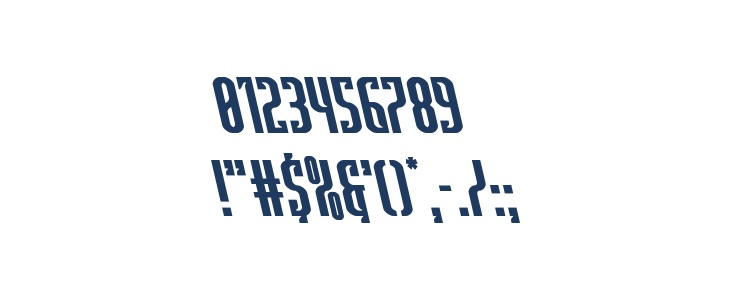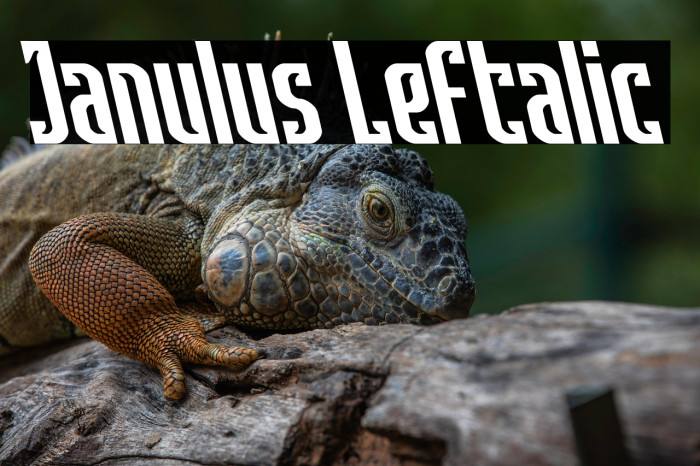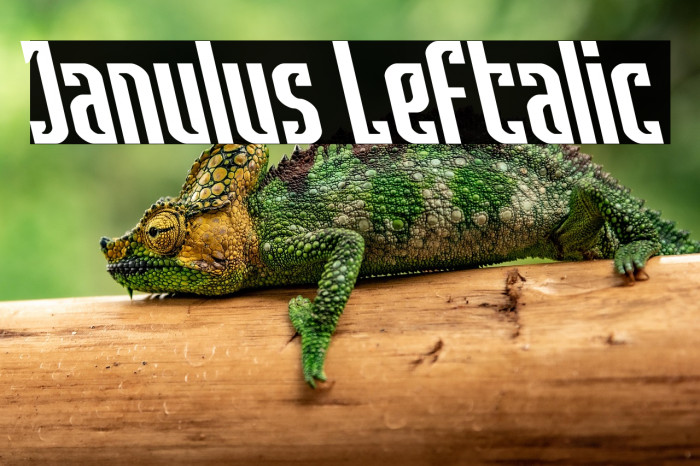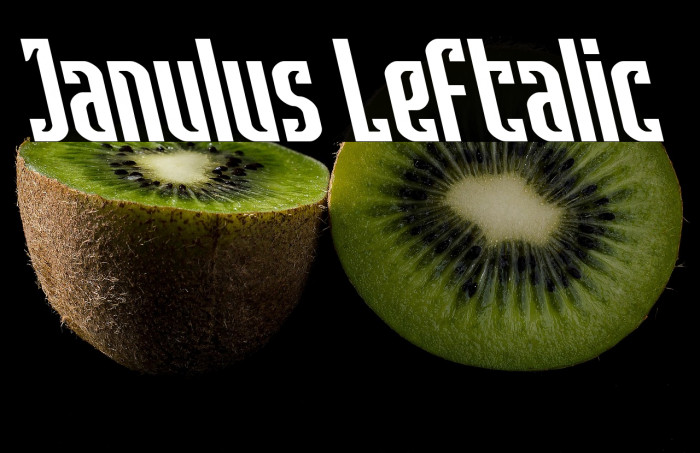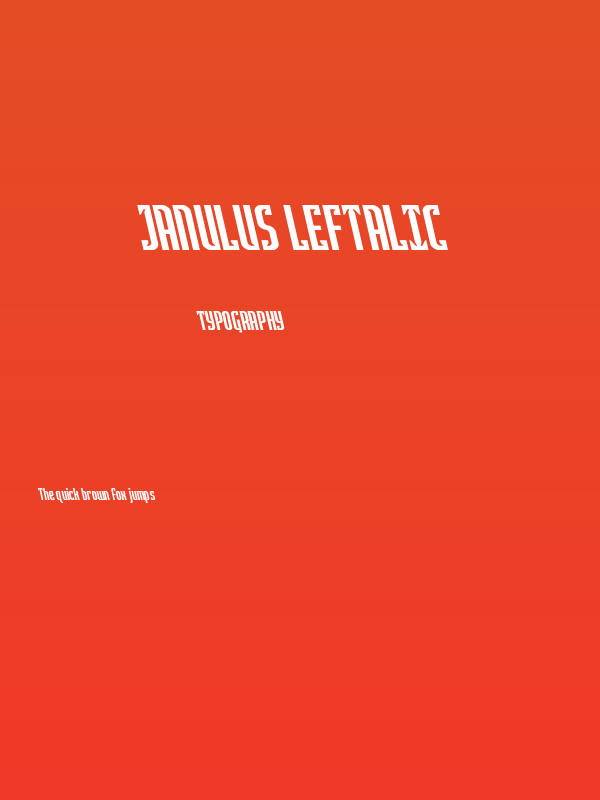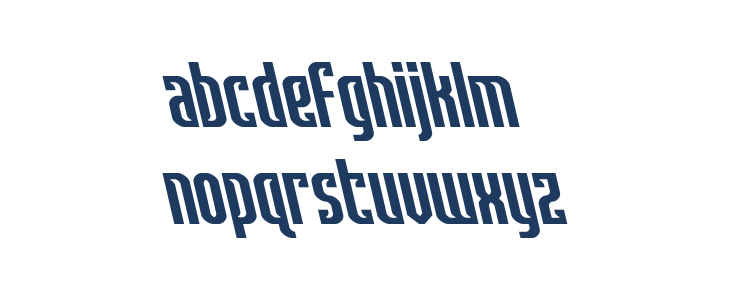
Janulus Leftalic Font
✎ Thick
| Vorgeschlagene Projekte | Ideal for posters, branding, and headlines that need a modern and dynamic look. |
Janulus Leftalic